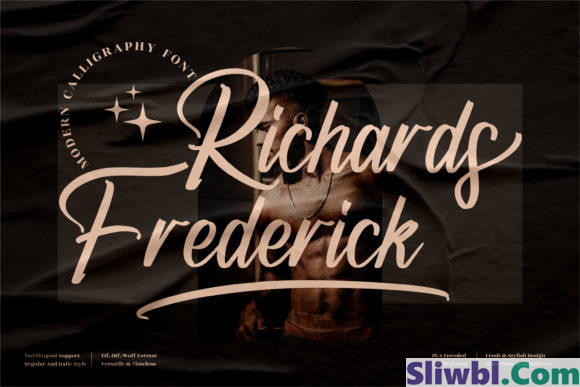
[Creativefabrica] Richards Frederick Font (2021)
Richards Frederick - это прекрасный шрифт с очаровательными, игривыми символами, которые словно танцуют вдоль базовой линии.
Этот шрифт закодирован PUA, что означает, что вы можете легко получить доступ ко всем удивительным глифам и лигатурам!